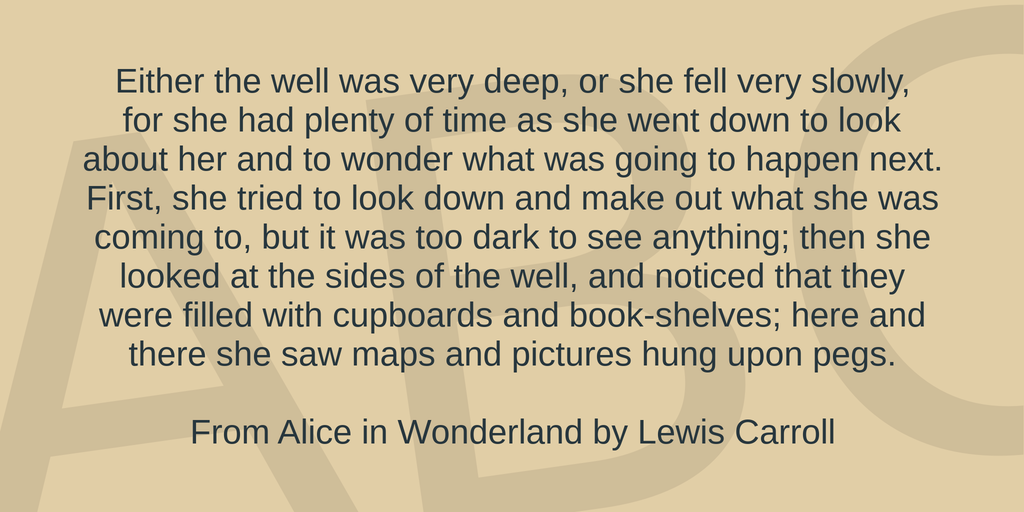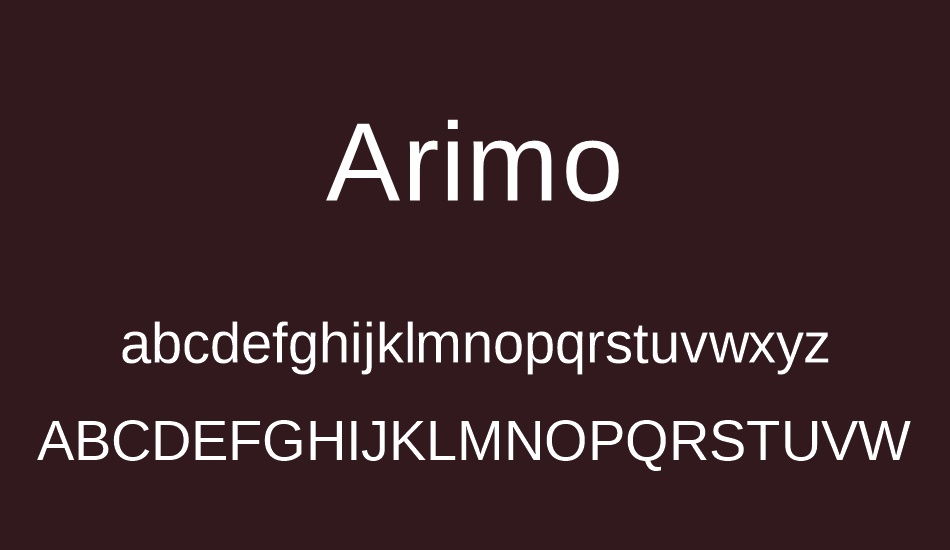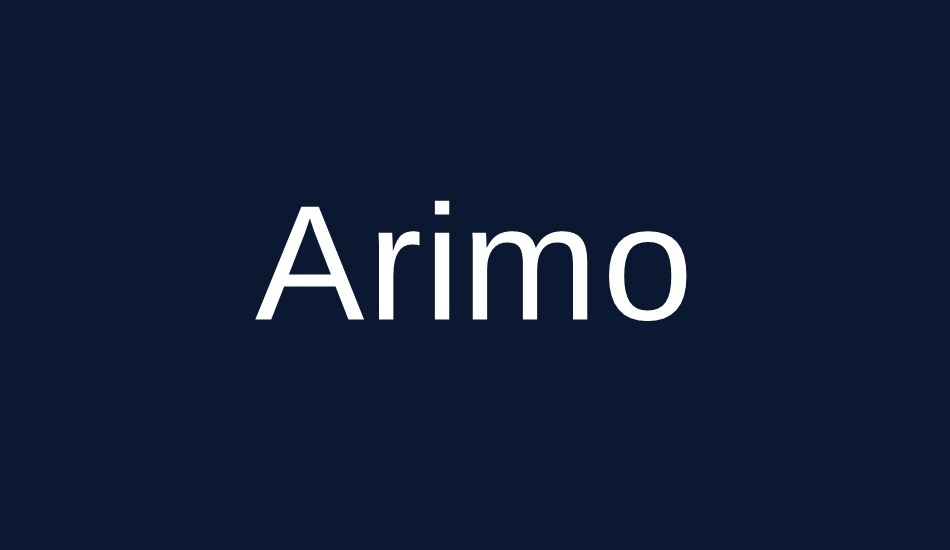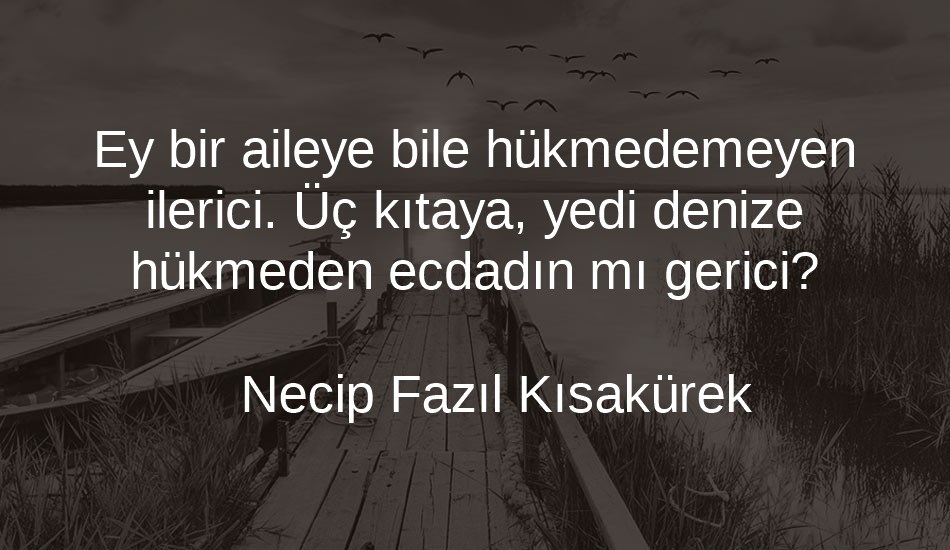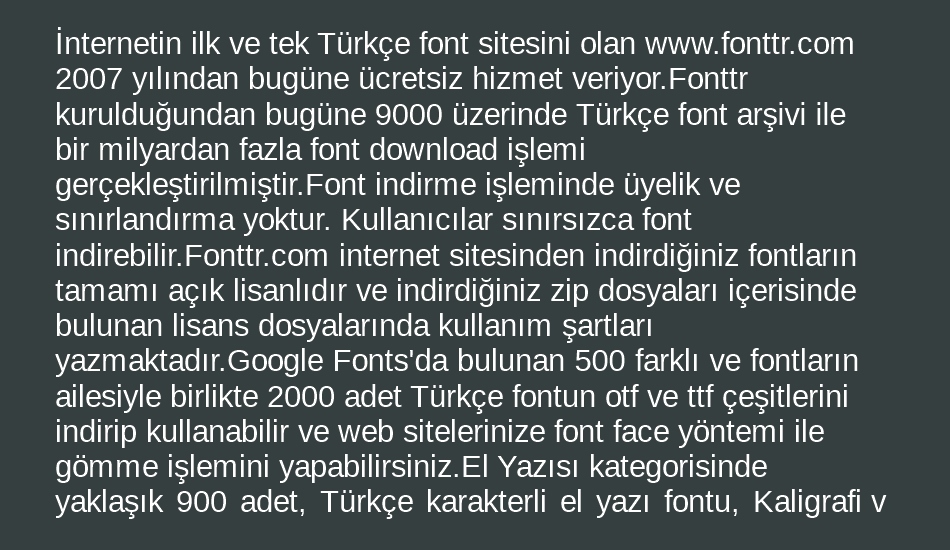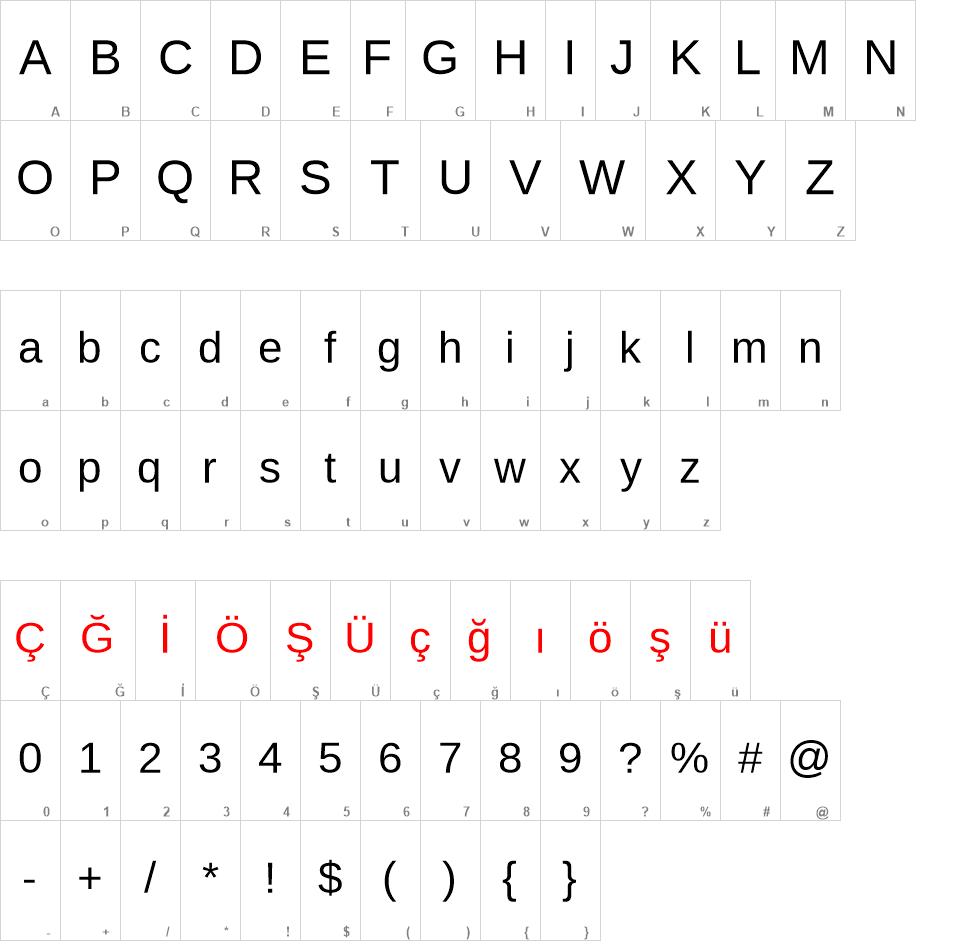
Helvetica, en yaygın kullanılan yazı fontudur.
Anlaşılabilir ve net olduğundan trafik işaretleri, uyarı levhaları, reklam metinleri, reklam panoları ve devletler arası yazışmalarda öncelikli olarak tercih edilen bir yazı karakteridir. Helvetica font ücretli bir yazı tipidir. Helvetica font yüzde yüz ücretsiz hali arimo fontudur. Zip dosyası içerisindeki arimo helveticanın 4 adet yazı tipi font family oluşturur. Helvetica Neue font download .
Arimo font